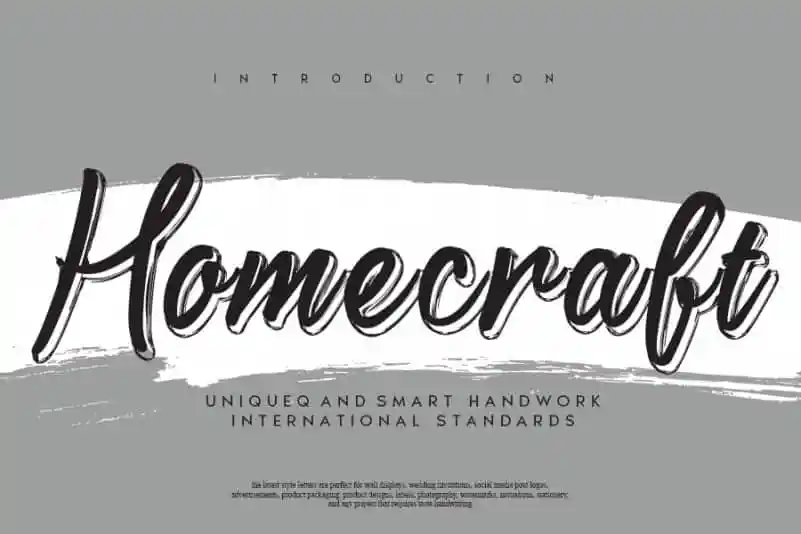
A Homecraft Script Font é uma fonte à mão escrita que caiu no meu coração. Com seu toque elegante, ela se destaca perfeitamente para seus projetos favoritos. Este estilo distintivo e eterno será a aposta certa quando você está procurando por um visual único e memorável em suas criações gráficas. É perfeito tanto para um texto leve e descontraído quanto para texturas mais elaboradas, garantindo sempre uma experiência única e imersiva. Seja você designer de arte digital ou freelancer de design, a Homecraft Script Font será sua escolha ideal para adicionar personalidade e sofisticação aos seus trabalhos.